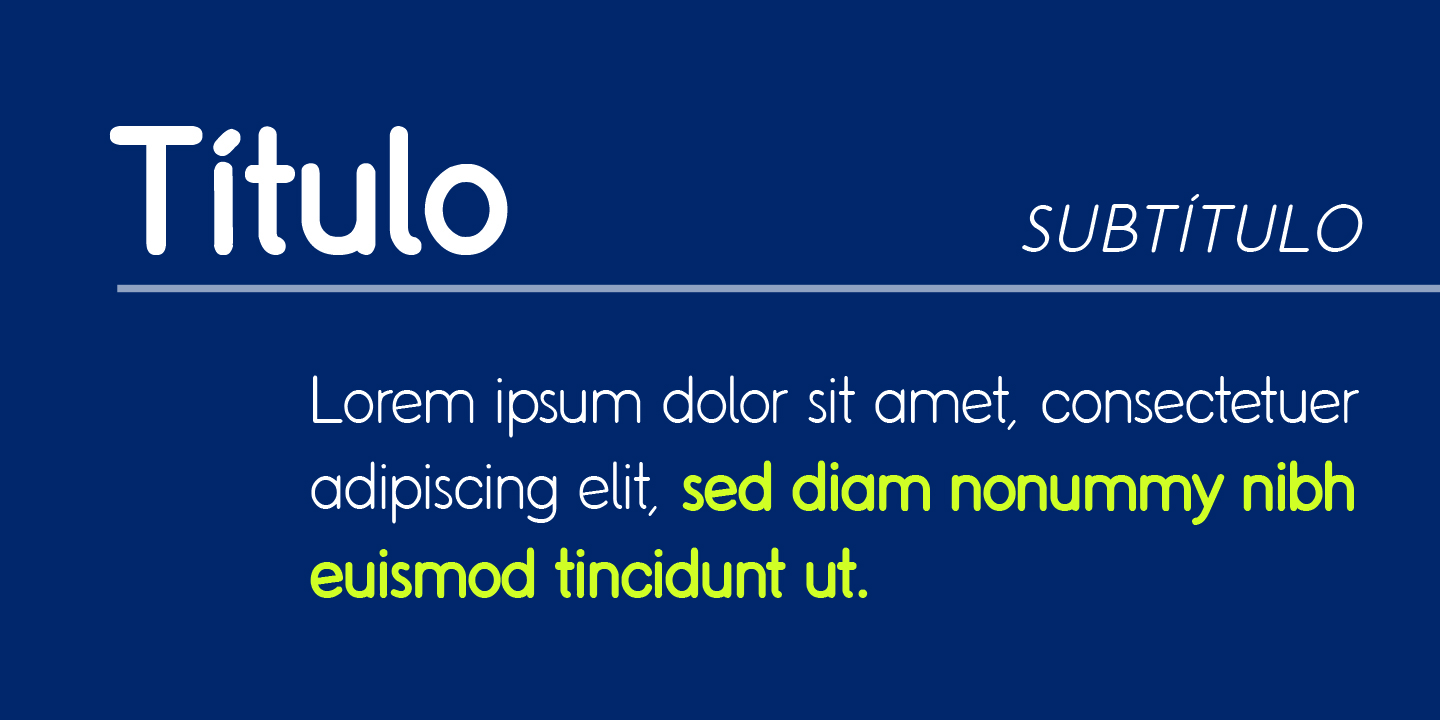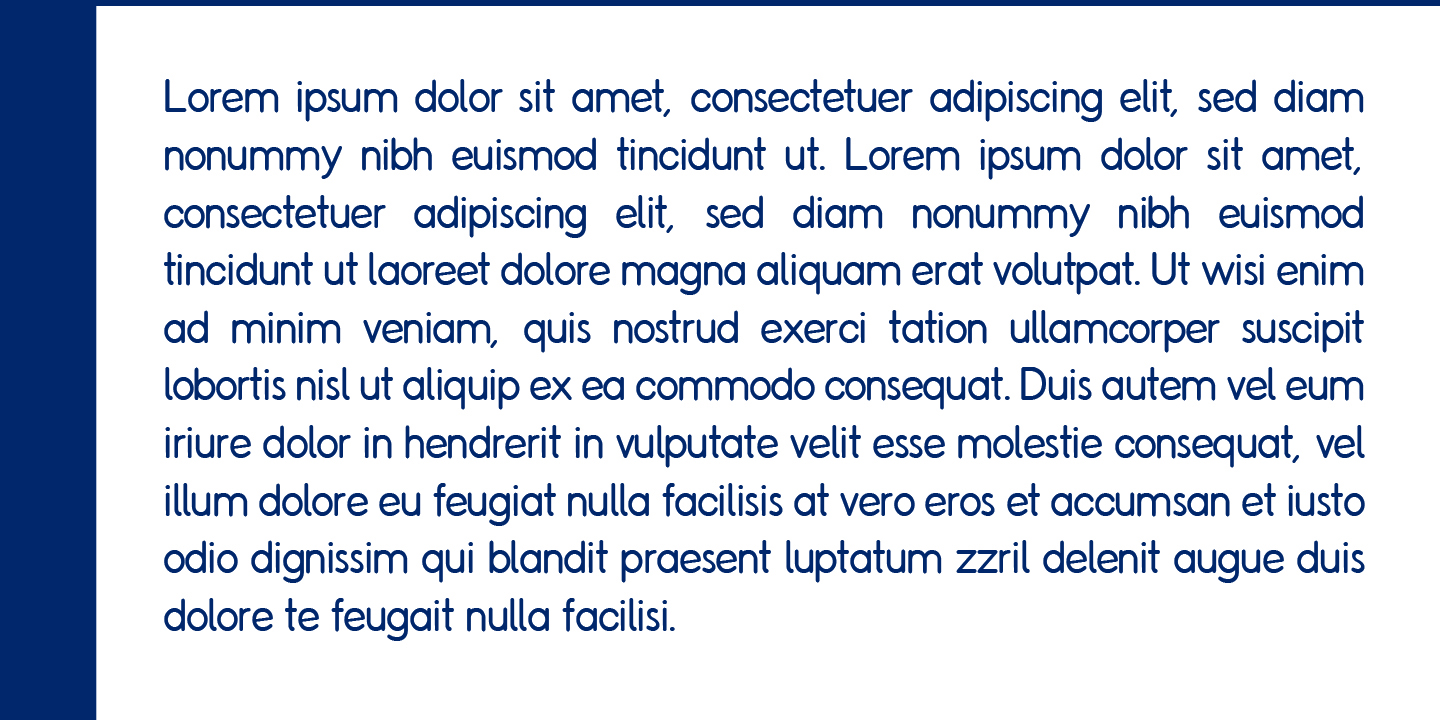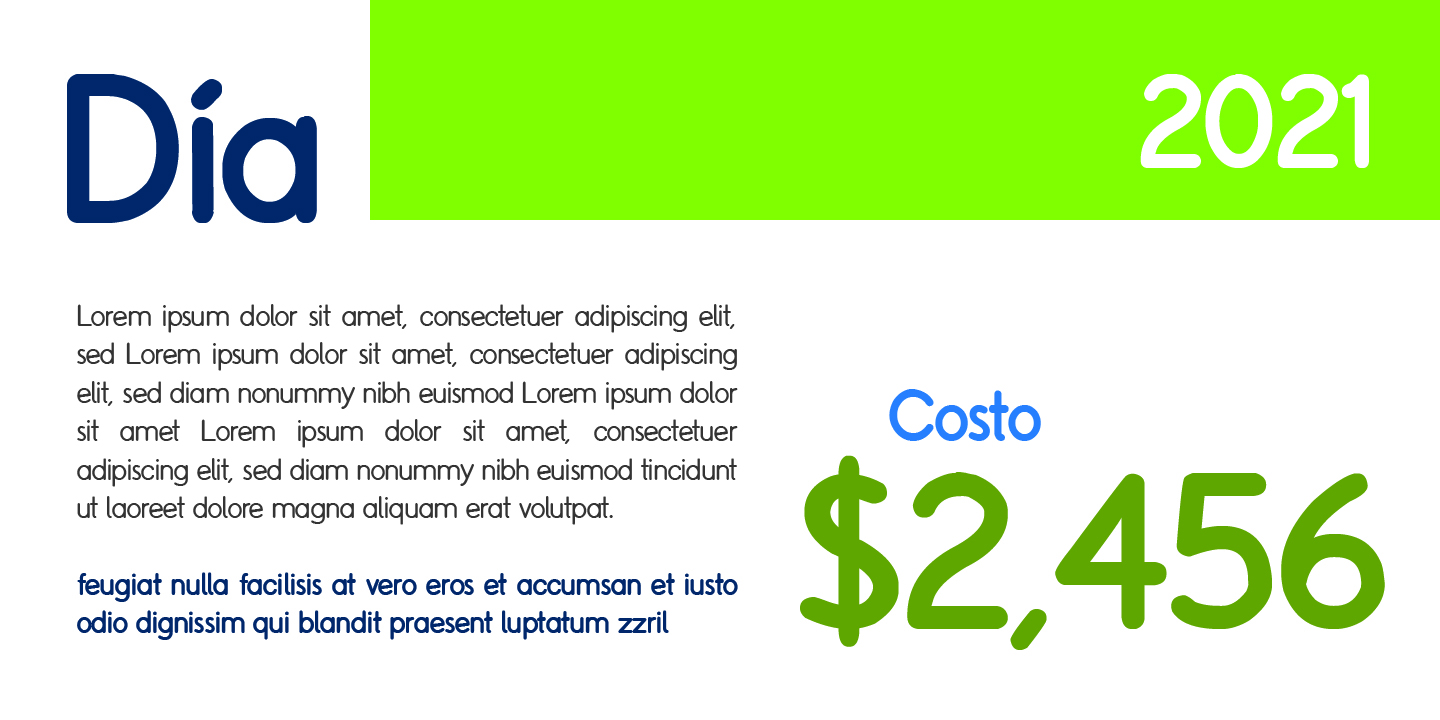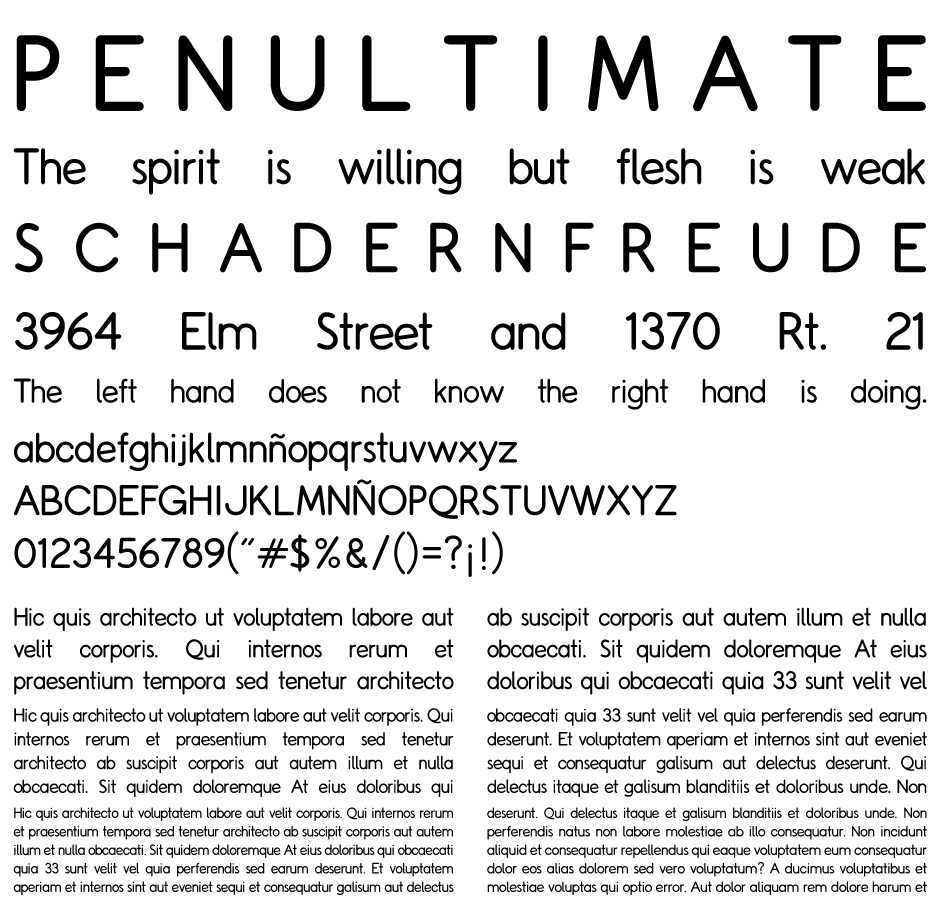
(2011) - La tipografía Copilme es la primer tipográfica creada por Ixipcalli, pionera en los estudios tipográficos. Su nombre proviene de los vocablos náhuatl «copilli» (tocado/corona) y el plural «meh», lo que significa «tocados o coronas».
Su diseño es un estilo informal y básica de remates redondos. En su inicio contó con solo un peso (regular), que al tiempo después se añadió la forma ligera y negrita. En septiembre 7 del año 2022 se ajustaron los márgenes entre caracteres, se añadieron mas elementos de acentuación, caracteres y las formas itálicas para generar una familia mas completa en la lectura, títulos o elementos gráficos. Ha sido empelada en banners, flyers, logos y textos informales.
Agosto 12 del 2025. Actualización de sustitución del caracter «a» minúscula romana por la «a» italica, esto con el fin de mejorar su aspecto en el uso de la escritura.
Septiembre 1, 2026. Se ha realizado una actualiazacion a la versión 4.0 donde se ha reformado todos los caracteres en ángulos y proporciones que mejora un aspecto visual simétrico. Se añadieron signos de acentuación para extender su uso a un multilenguaje y el peso «heavy». Además se recuperó nuevamente la «a» griega como selección alternativa.